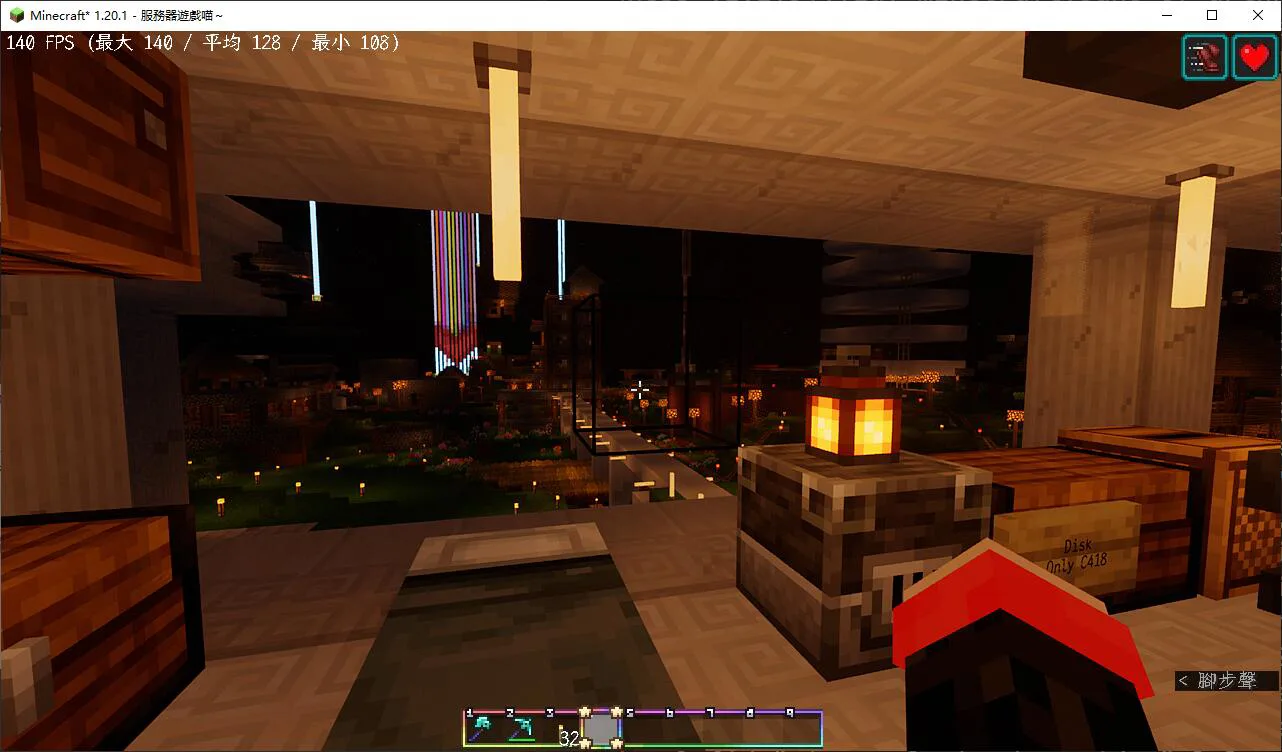
【字体】霞鹜文楷 ( lxgw-wenkai )
Этот ресурспак заменяет стандартный шрифт Minecraft на более чёткий и стильный шрифт Lxgw Wenkai, улучшая читаемость текста в игре.
Ресурспак основан на шрифте Lxgw Wenkai версии 1.520 и был адаптирован для Minecraft с разрешения автора. Он заменяет стандартный шрифт игры на более чёткий и элегантный, что делает текст в интерфейсе и других элементах более читаемым и визуально приятным.
Стиль шрифта Lxgw Wenkai придаёт игре уникальную атмосферу, сохраняя при этом совместимость с указанными версиями Minecraft. Ресурспак не влияет на производительность игры и легко устанавливается, предоставляя простой способ кастомизации текста без изменения других аспектов геймплея.